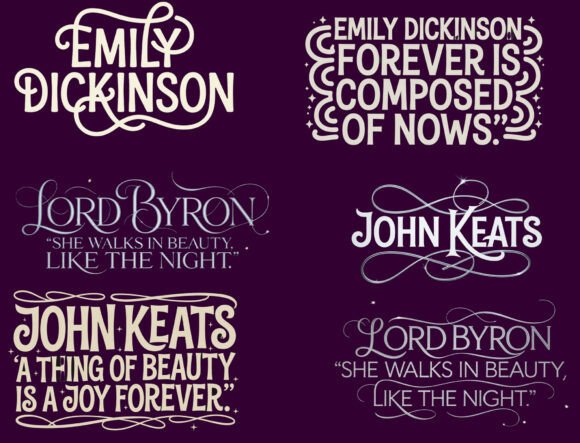
Retro Mood – Bold Vintage Font T-Shirt
Doğru tasarım öğelerini bulmak zor olabilir, ancak Retro Mood – Bold Vintage Font T-Shirt, çalışmanızı anında bir üst seviyeye taşıyan olağanüstü bir koleksiyon sunar.
Hassasiyetle hazırlanan Retro Mood – Bold Vintage Font T-Shirt, temiz vektörler, pürüzsüz tipografi ve içinizin rahat etmesi için ticari bir lisans sağlar.
İster İsteğe Bağlı Baskı (POD) ürünleri, ister düğün davetiyeleri veya sosyal medya grafikleri oluşturuyor olun, Retro Mood – Bold Vintage Font T-Shirt ideal bir uyumdur.